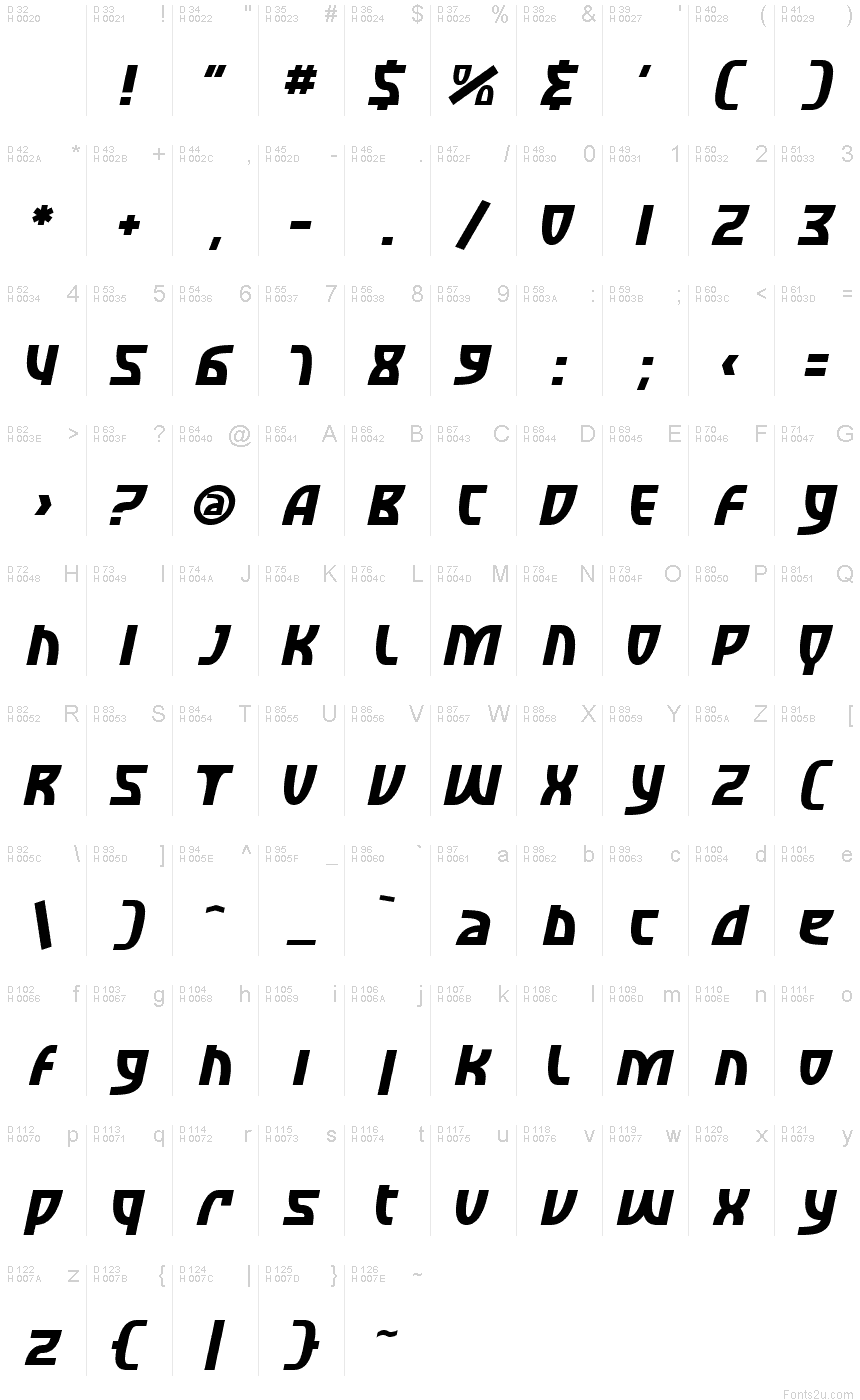
SF Retroesque Oblique
SF Retroesque Oblique von ShyFonts Type Foundry ist eine kostenlose Retro-Display-Schrift mit dem Flair der späten 70er Jahre und einem stromlinienförmigen, fast schon futuristischen Sci-Fi-Schwung. Die Buchstaben sind stark geneigt und breit gestaltet, wobei stumpfe Ecken auf weiche Kurven treffen – das Design wirkt dynamisch, kompakt und leicht futuristisch, ohne seinen Vintage-Billboard-Charakter zu verlieren.
Sie eignet sich perfekt für Poster, Arcade-inspirierte Brandings, Albumcover, Titelkarten und Event-Flyer, bei denen eine kostenlose Schrift mit einer selbstbewussten Note überzeugen soll. Setzen Sie sie für Logos, Cover-Texte und andere kurze Display-Anwendungen ein, bei denen die Kursivneigung und die breiten Formen selbst einfachen Wörtern eine pulsierende, maschinelle Energie verleihen.